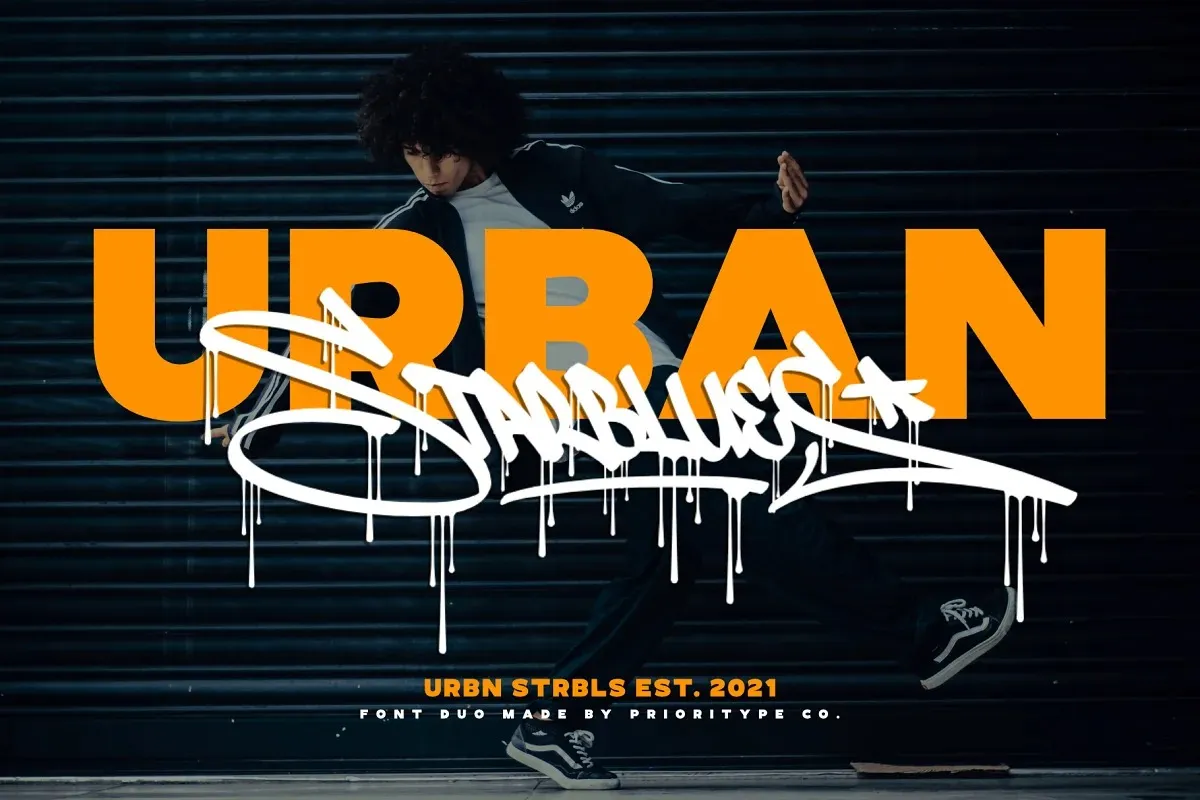
Urban Starblues Font – Fonte Grátis
Urban Starblues Font
A Urban Starblues Font é uma descoberta perfeita para designers buscando inspiração na arte urbana das grandes cidades. Inspirada nos carimbos de rua, essa tipografia script é perfeitamente adaptada para diversos projetos, desde camisetas e posters até capas de produtos e thumbnails de vídeos. Perfeito para aqueles que valorizam a arquitetura da cidade em suas criações visuais, a Urban Starblues traz um toque único ao seu design, tornando seus trabalhos ainda mais especiais. Com este fonte na sua arsenal, você poderá explorar novas maneiras de incorporar o espírito vibrante e orgânico do mundo da rua em suas obras. Sem dúvida, uma excelente adição para qualquer designer buscando um elemento único no seu trabalho.